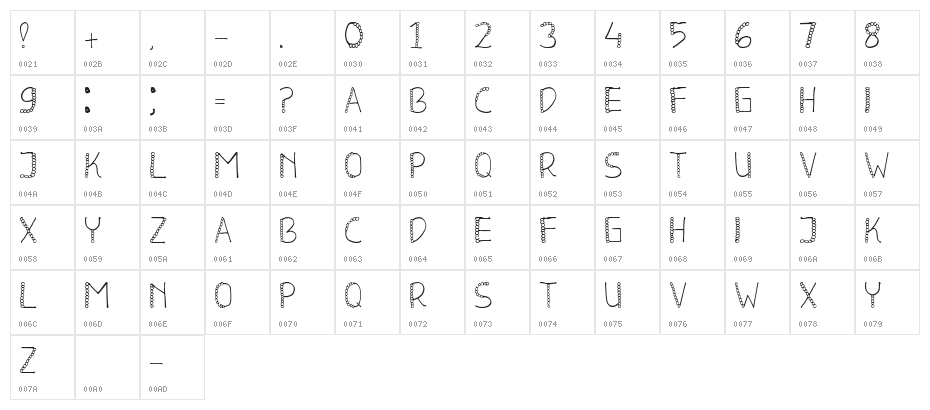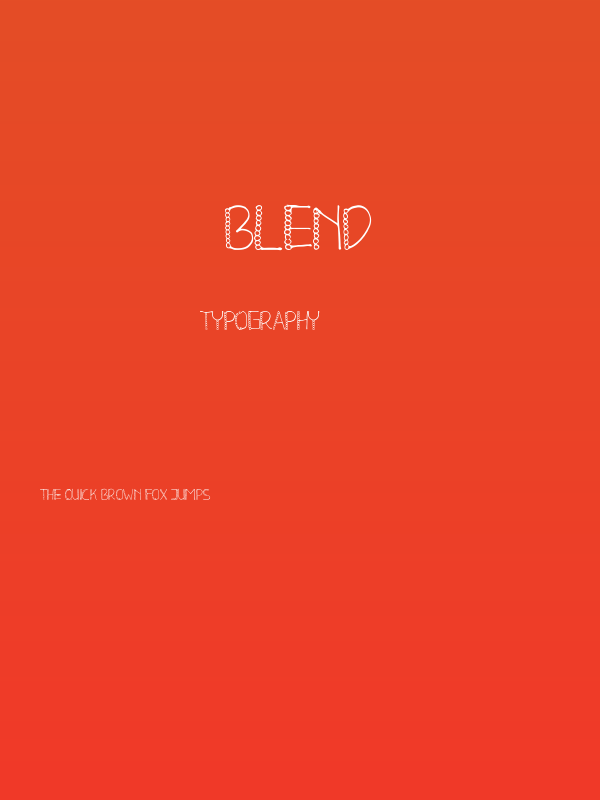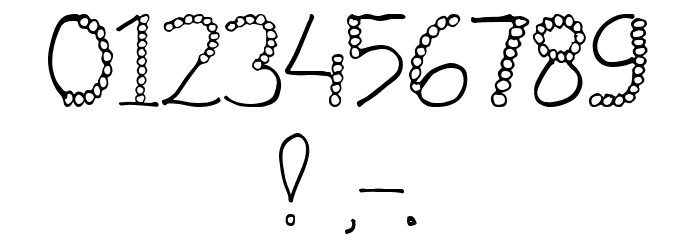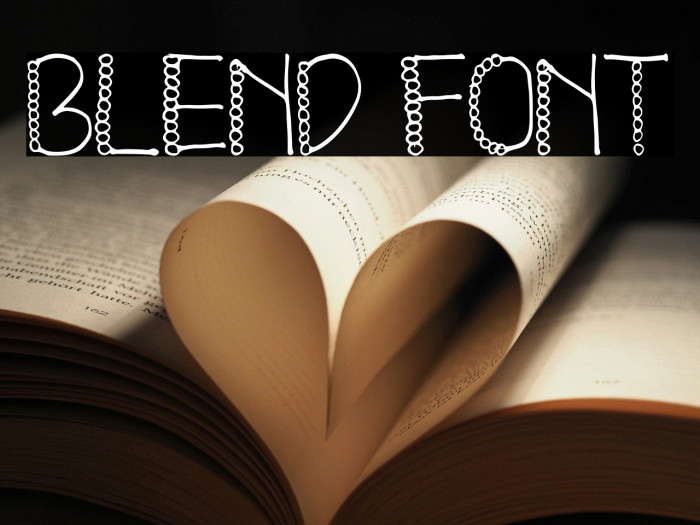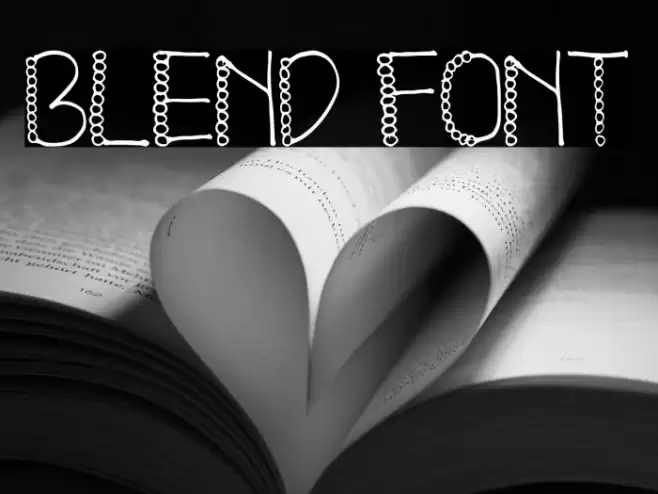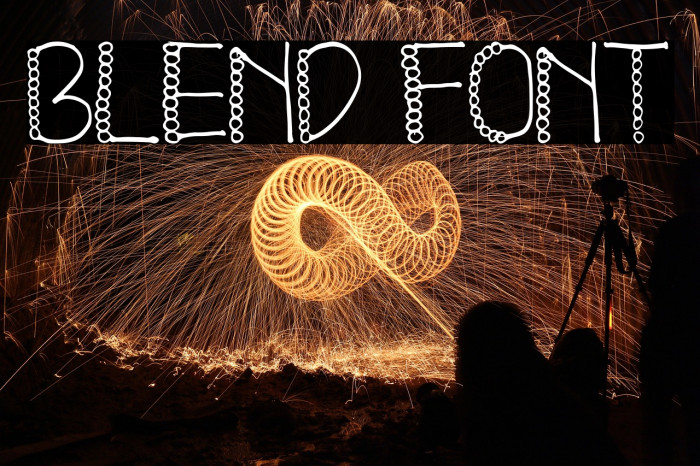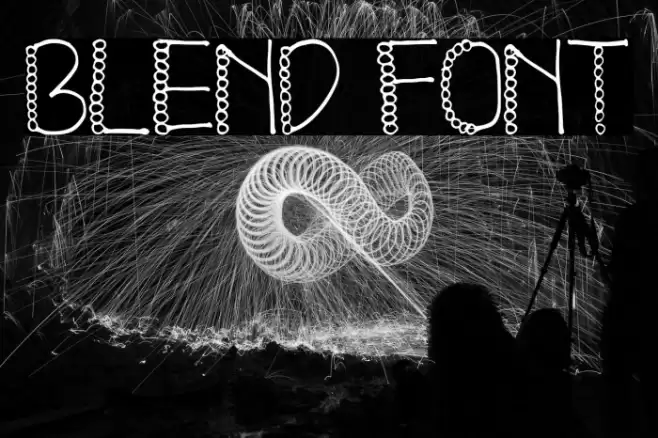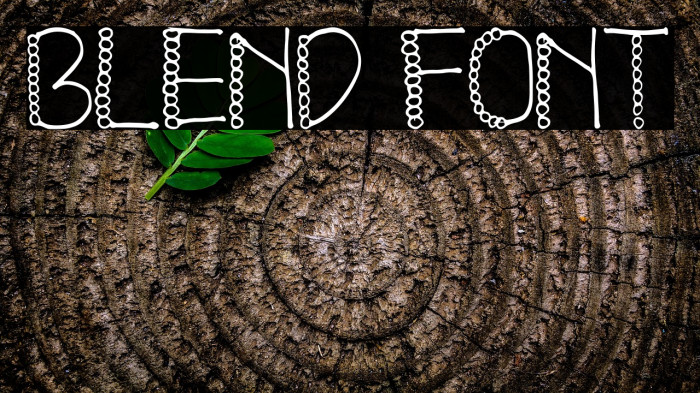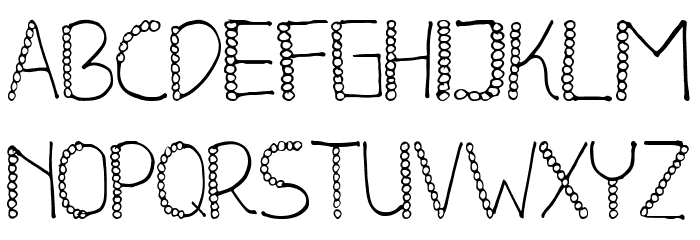
BLEND Font
| Stile generale | Whimsical, Playful, Decorative |
| Caso d'uso | Headlines, Logos, Creative Projects |
| Progetti proposti | Ideal for children's books, party invitations, playful branding, and creative posters. |